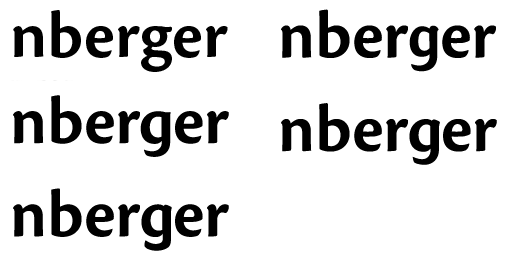
Doppelstöckiges g ändern (Cronos Pro)
ich gestalte gerade ein Logo, die Wortmarke soll in der Cronos gesetzt werden.
Das doppelstöckige kleine g fällt bei dem Wortbild extrem auf, ich würde es gerne in ein einfaches g ändern. Ich habe nun das kleine q modifiziert und das ist dabei rausgekommen. Was haltet ihr davon? Ich tue mich deshalb so schwer, weil ich keine vergleichbare Schrift (mit angedeuteten Serifen) und dem einfachen g kenne.
Wer gibt mir Tipps oder will mir die ganze Aktion vielleicht ausreden? Müsste ich dann aus Konsequenz auch das kleine a ändern? Ich würde sagen: Nein, denn bei der Helvetica ist auch ein traditionelles a und ein einfachs g gestaltet worden.
Ich würde mich über Anregungen zur Gestaltung freuen! Danke und Gruß, Martin
Ich würde den oberen Bogen vom "g" etwas niedriger machen. Dann passts.
Ich habe mal die Officina als Beispiel genommen:
Ist das bereits das originale Wort? Und sollen es Kleinbuchstaben sein? Durch die beiden ›er‹ erhält der Name etwas Symmetrisches, das ihm die Spannung nimmt. Daran ändert auch das neue ›g‹ – das ich ansonsten gut anempfunden finde – nicht viel. Vielleicht könntest Du, falls das geht, etwas mehr wagen: die Unterlänge zu einem Bogen ausziehen o. ä. – irgendetwas, was dem Wort ein bisschen Spannung gibt.
"erger" ist nicht das ganze Wort, es ist ein Ausschnitt aus (...) Nürnberger (...).
ich habe jetzt mal versch. Variationen ausgearbeitet, welche findet ihr am besten, welche sollte ich tweaken. Ich bin im Moment für die Version "zweite Zeile rechts".
Was meint ihr? Oder doch ganz anders?
Ich wuerde ja rein gefuehlsmaessig auf die Variante in der ersten Zeile rechts setzen.
Hallo, Danke für die Einschätzungen. Das q der Cronos sieht aus wie "zweite Zeile links", nur mit gerader Unterlänge.
erste zeile rechts finde ich nicht passend, das erste was du aus q gemacht hast,
passt zu cronos am besten, ausserdem gibt es bei cronos swash italic ein g in dieser richtung.
Typografiski, Danke für das Bild und den "stiltreuen" Hinweis. Ich kann so gut weiterarbeiten.